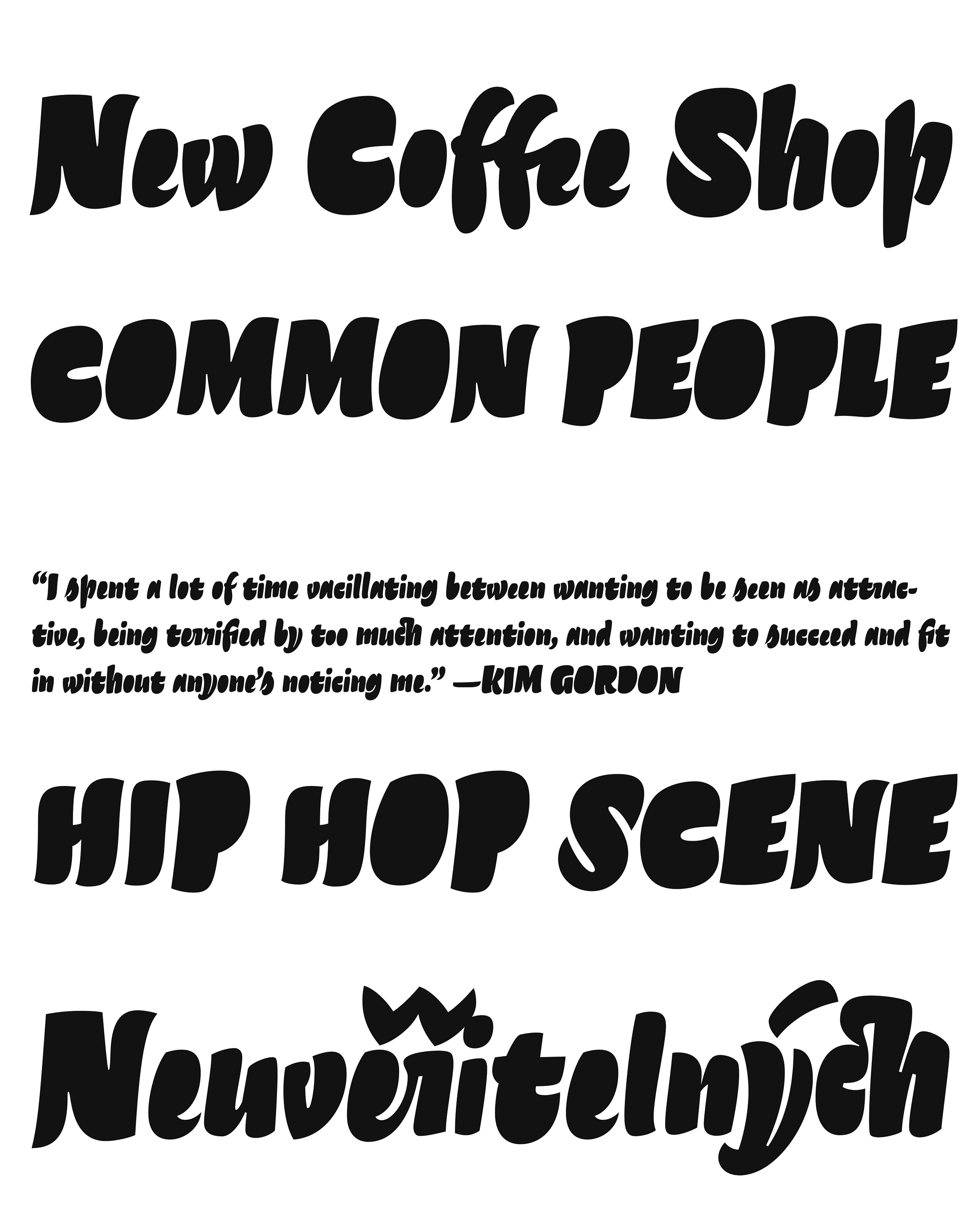
| Créditos | Francisco Gálvez Pizarro, Javier Quintana Godoy, Guido Ferreyra |
| Descripción | Sin contraformas cerradas, Chupilca es un ejercicio de ritmo y audacia, una tipografía expresiva, tosca y cursiva, ideal para logotipos o titulares que buscan una estética desenfadada y atrevida. La fuente base es Chupilca Fat, que incluye una capa de sombra extruida llamada Chupilca Background. Ambas fuentes incluyen numerosos caracteres alternativos y contextuales, así como ligaduras estándar y discrecionales. |
| Clasificación | Títulos, Experimental |
| Familia(s) | Chupilca-Fat, Chupilca-Background |
| Estilos | 2 |